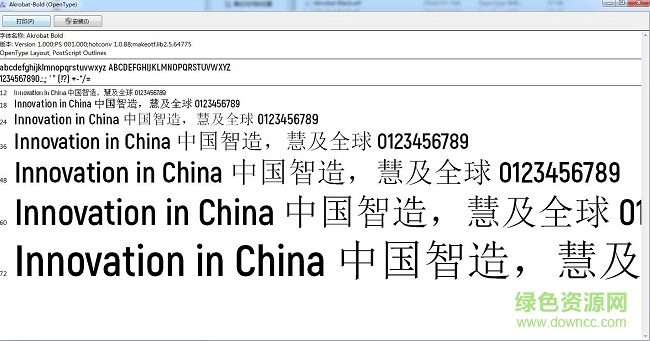
akrobat bold/semibold/black/extrabold字體包
akrobat字體包是本站為大家整理的免費英文無襯線字體合集,收錄了akrobat regular、akrobat bold、akrobat extrabold、akrobat black和akrobat semibold五款字體,從細到粗全都有,歡迎需要的朋友前來下載!
akrobat bold